行书是在隶书的基础上发展起源的,是一种介于楷书和草书之间的字体。它的出现时为了弥补楷书的书写速度太慢和草书的难于辨认而由来的。行书的“行”是“行走”的寓意,所以他不似草书般潦草不易 字体识别,也不似楷书的端正。因此潦草的行书也被称为“行草”,端正的行书被称为“行楷”。
这次要给大家推荐几款的不是“行草”也不失“行楷”,而是行书字体。
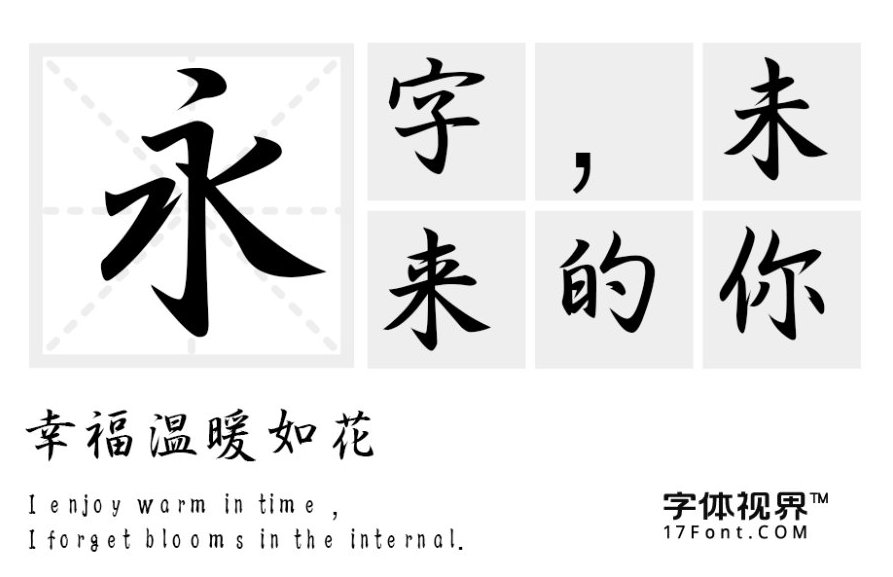
三极行书简体:这款字体结构紧凑,笔画写意,线条衔接张弛有度,遒劲有力。在传统行书上进行创作后,实用性和艺术性皆备。适用于印刷媒介的标题与正文排版、各类屏幕显示以及影视字幕、游戏、招牌设计等。
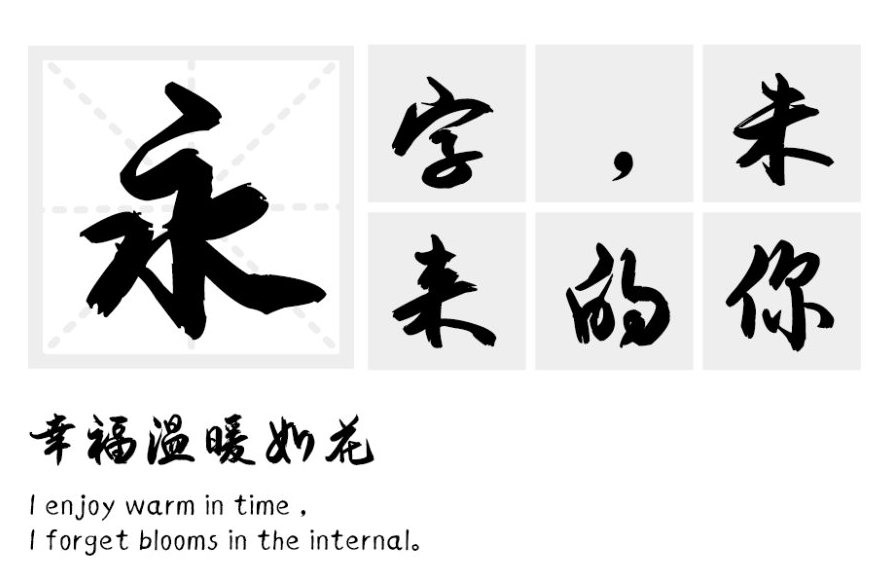
安景臣毛笔行书:用毛笔书写的行书蕴涵深厚的传统功力,在传统行书的基础又融入了新时代的审美气息。字形规范却不失特色,严谨秀美透出从容优雅的态度。赏心悦目,百看不厌。用于logo设计、招牌设计和影视、标题都非常合适。
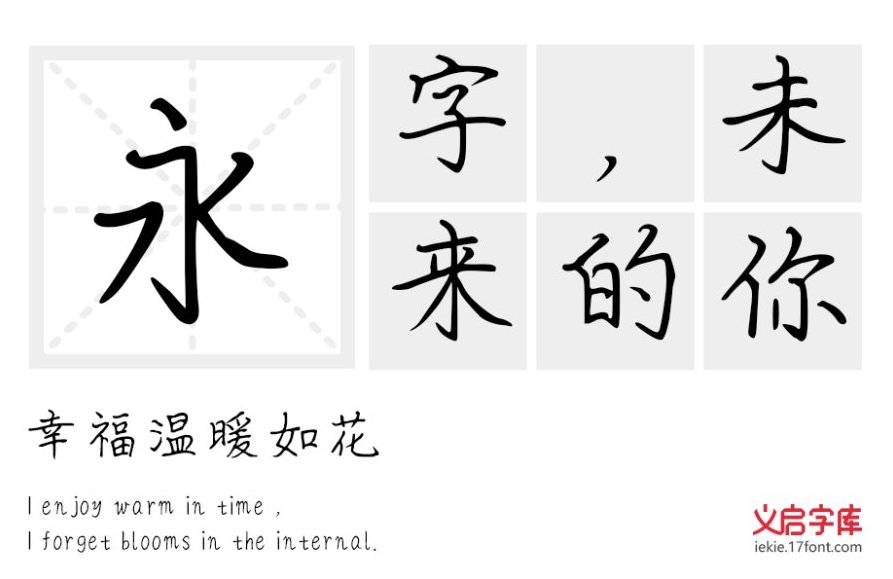
这款行书字体是由中国书法家协会会长、国际书画研究会终身会员兼全国书法大赛评委刘圻大师亲笔所写的“义启刘圻硬笔行书” 。 图片字体 笔法精湛干练,随性却又显示出高深的书写功力。富有力度和余势,收笔尖锐饱满,虚实变化平衡。